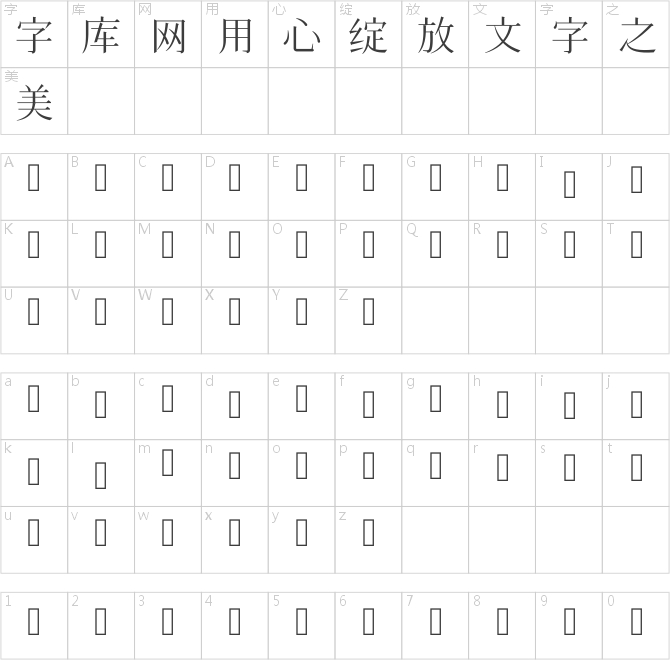
花園明朝
花園明朝介紹
日本花園明朝體在免費字體中算是非常非常好的一款了,花園明朝 (Hanazono) 是一個免費字體,為 GlyphWiki 所研發,字形數量共 45090 + 47186 個,幾乎收錄了所有漢字字形(但看起來沒有區分不同地區標準字形)。 一共收錄了八萬多漢字的免費字體,本次發布的是八萬漢字完整版。 第一步這個字體的輪廓是用 CHISE 計劃的影系統生成的,數據來源就是 Glyphwiki,因此可以在相對短的時間內生成N多的文字(貌似今年剛補完日本的戶籍統一文字),但是影系統生成的筆畫輪廓實在是不敢恭維,其避讓系統也不算很完善,不能用來生成很粗的字。